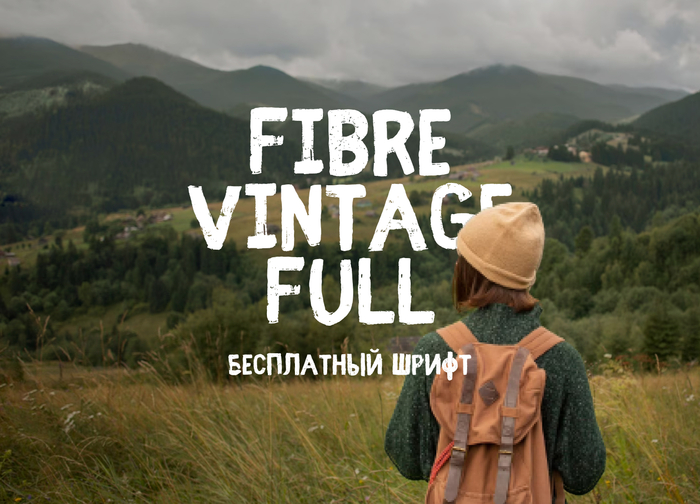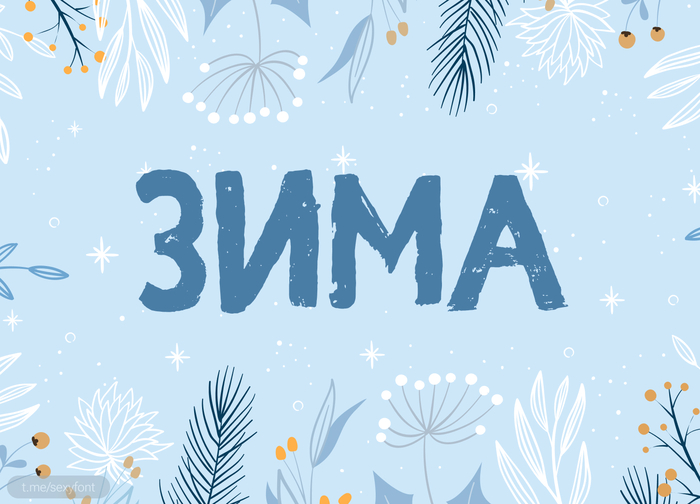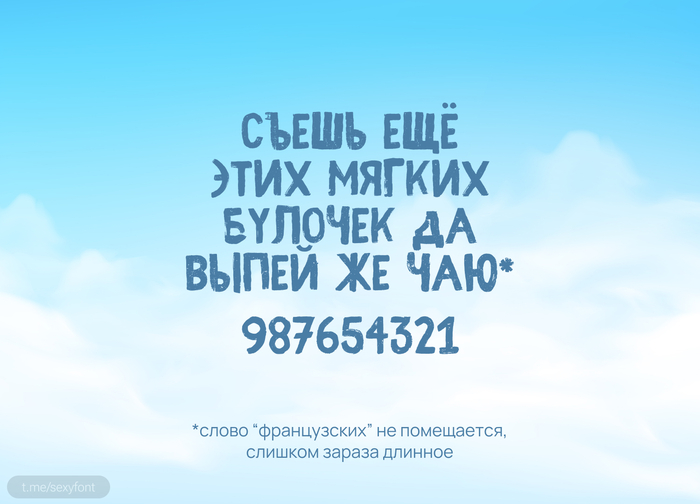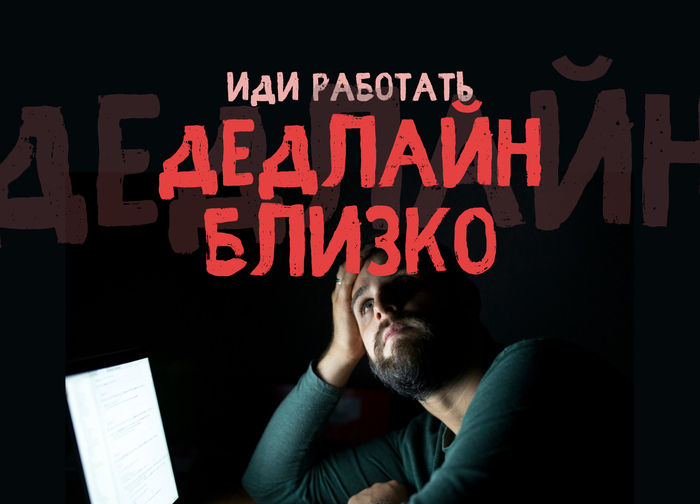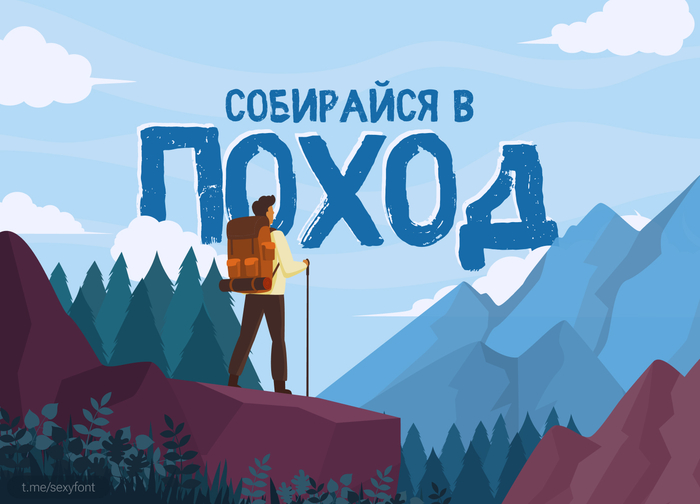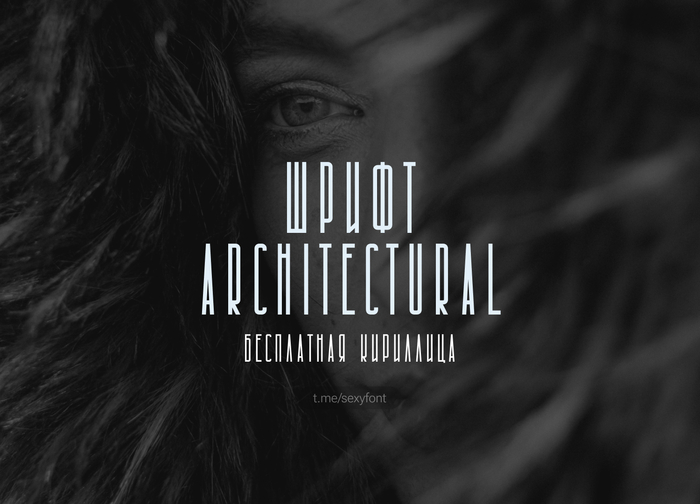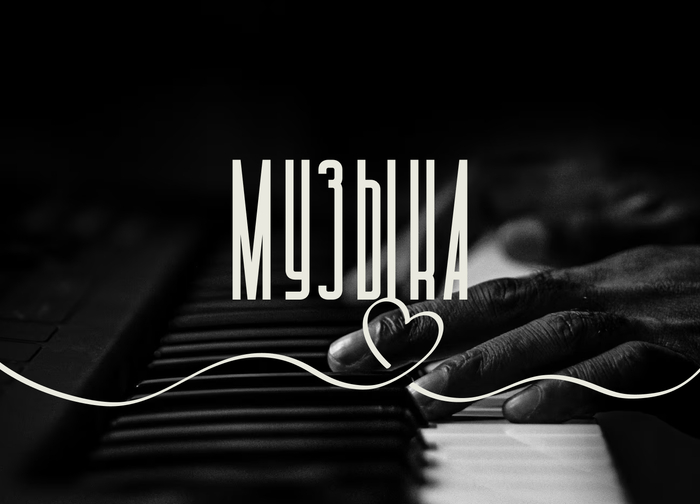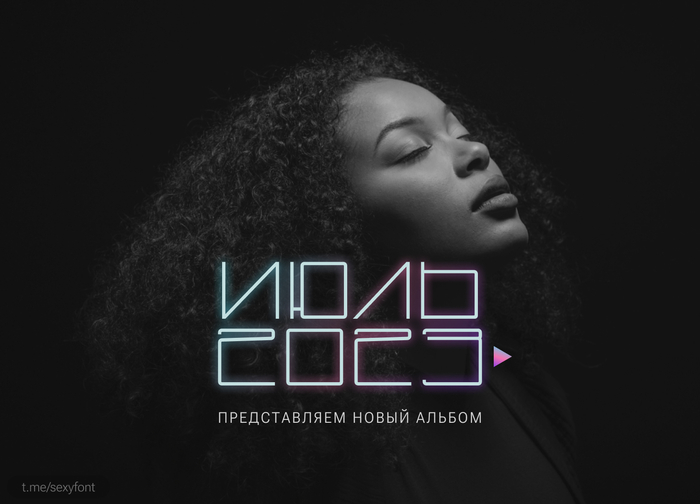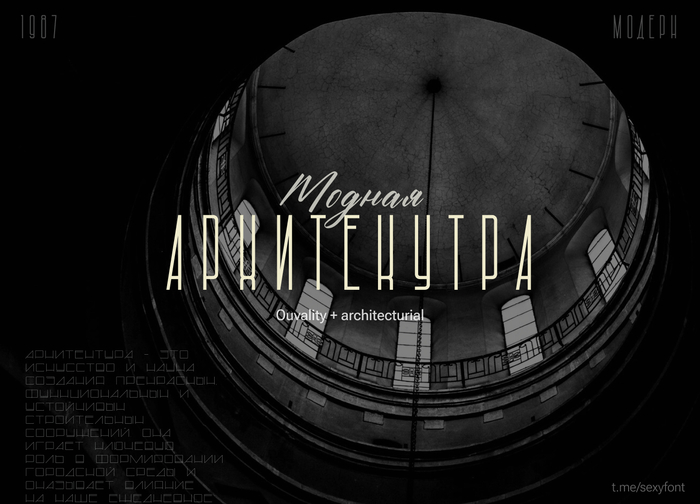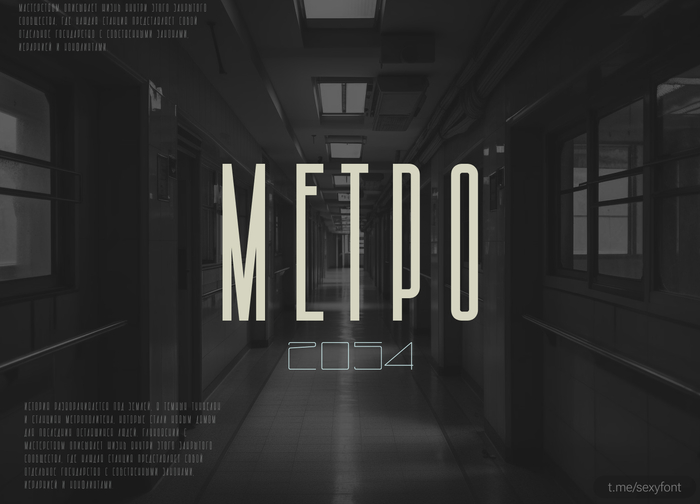
Кириллические шрифты
Новая презентация шрифта)
Fibre vintage full рукописный винтажный шрифт, все основные символы уникальны и не один не имеет тот же шум. Отлично впишется под крупные заголовки. Бесплатно для личного использования. Автор: Krisjanis Mezulis.
Высоченный шрифт Architectural
Читаемость конечно на грани, но все же для каких-нибудь коротких декоративных надписей подойдет) Не так уж много у нас высоких и компактных шрифтов. А еще у него есть много начертаний и вариативность) Можно настраивать как ширину букв, так и толщину.
Шрифт tex gyre bonum
Презентация шрифта tex gyre bonum. Бесплатная антиква для личного и коммерческого использования. Хорошо читаемая, имеет 4 начертания, включая курсив) Прошу любить и жаловать.
Бесплатный шрифт beer money
Деньги на пиво. Или Beer money. Веселый, рисованный шрифт. По стилю как-будто начеркали фломастером. Даже при таком уровне декоративности вполне читаем в заголовках и небольших абзацах. Но лучше не злоупотре-блеатъ.
Шрифт EuropeExtendedC
Футуристичный кириллический шрифт. Этот шрифт старше многих читателей) разработан в фирме TypeMarket в 1992-1993 (дизайнер А.Кустов)
Новая презентация. Шрифт Morfin
Изящная декоративная гарнитура, навеянная американскими шрифтами 70-х годов. Трекинг конечно не особо ровный) Но сильно придираться к полностью бесплатному шрифту не буду.